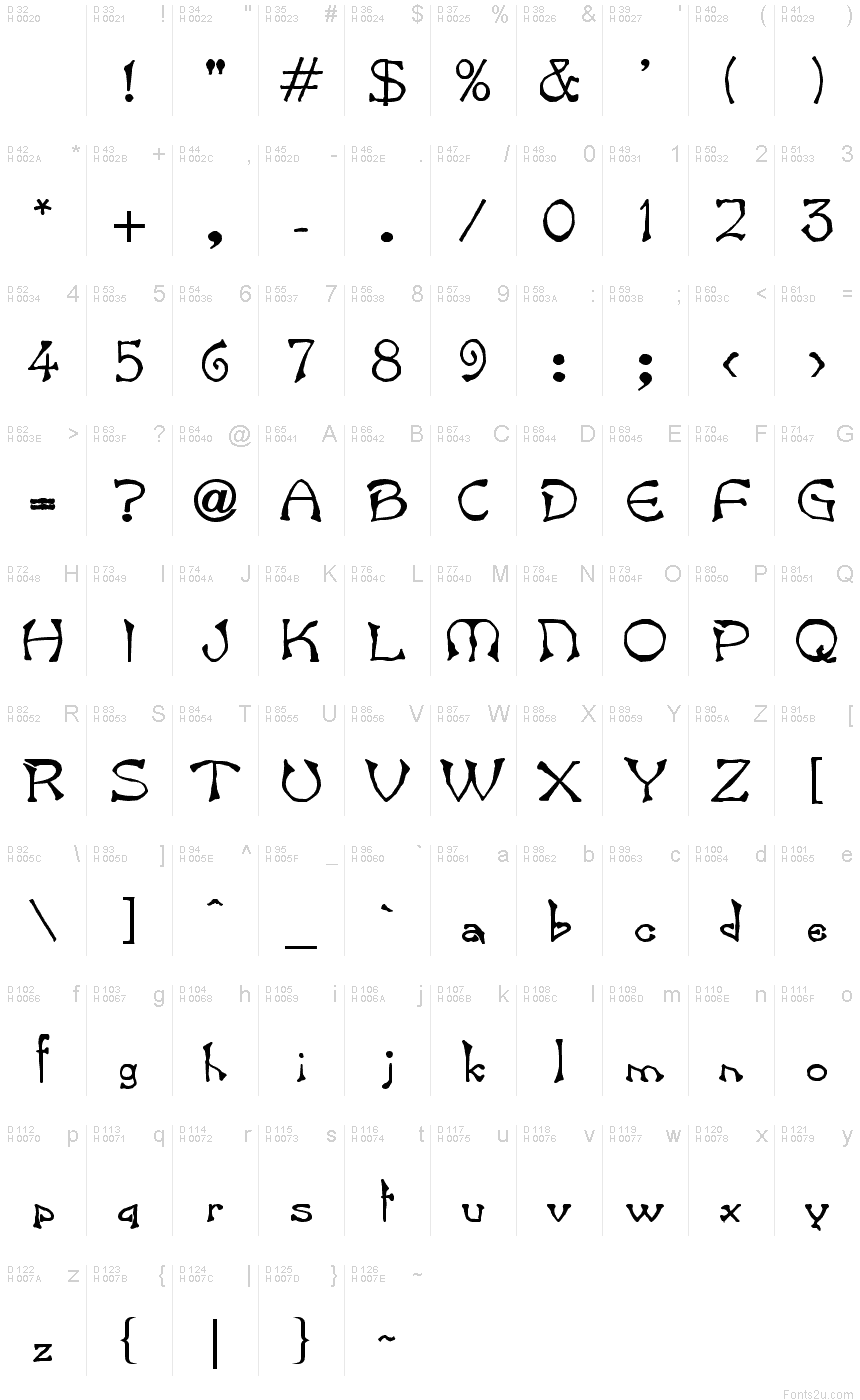
Krój pisma Bart Bold wniesie do Twoich nagłówków energię rodem z sobotnich kreskówek – z grubymi pociągnięciami i lekko rozmazanymi, atramentowymi krawędziami, które wyglądają, jakby zostały namalowane ręcznie w pośpiechu. Jako członek rodziny Bart, ten font ma zadziorny rytm i nieco nierówną grubość, dzięki czemu słowa zyskują życie, zamiast wyglądać sterylnie. Bart Bold to bezpłatny dekoracyjny font, który sprawdzi się wszędzie tam, gdzie chcesz od razu wywołać efekt „wow”.
Bart Bold świetnie sprawdza się w komiksowych nagłówkach, projektach naklejek, zaproszeniach na dziecięce imprezy, grafikach na gadżety, miniaturach na YouTube, szkolnych plakatach, ulotkach w stylu retro czy wyrazistych opisach do mediów społecznościowych. Ustaw go nieco większym, aby szorstkie kontury pozostały ostre, a w tekście głównym połącz go z czystym krojem bezszeryfowym, takim jak Helvetica lub Inter – Bart Bold robi szum, a bezszeryfowy font dba o czytelność.